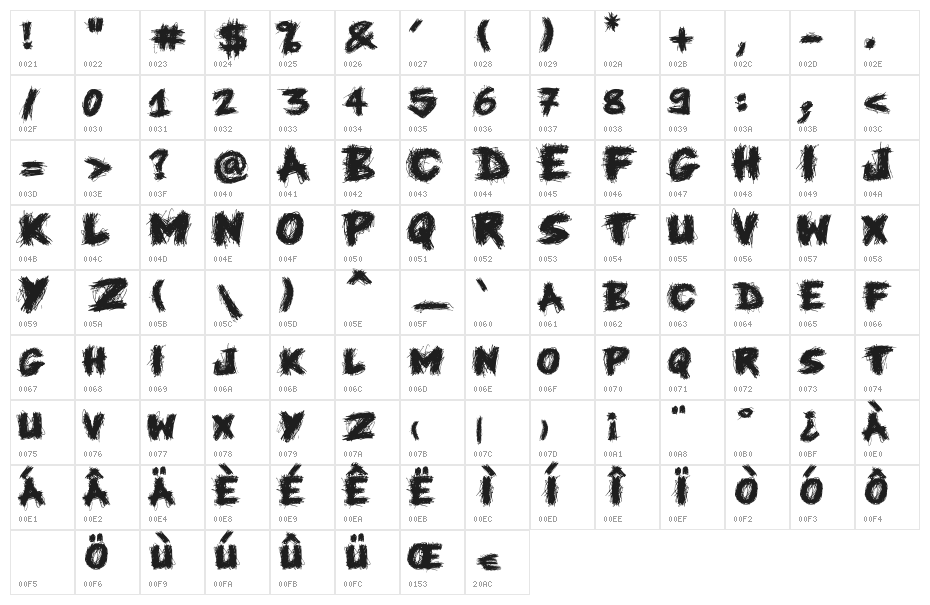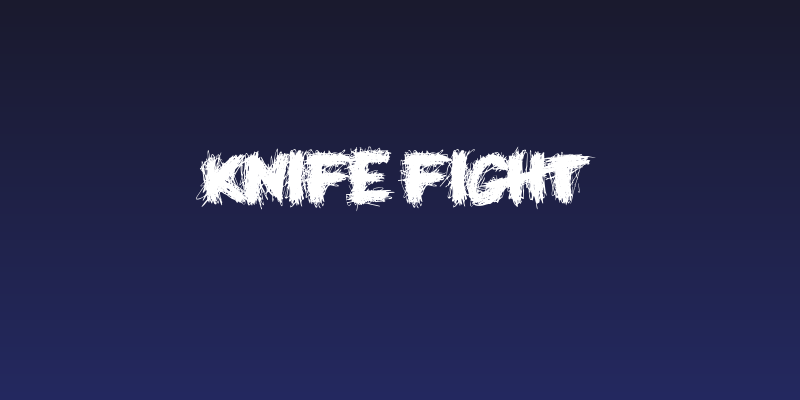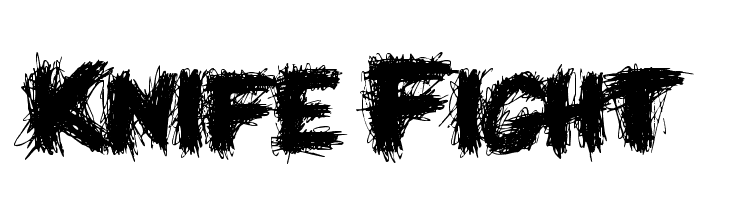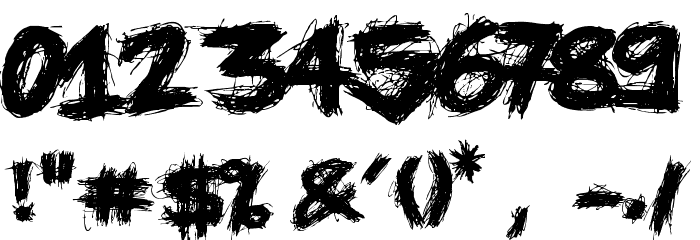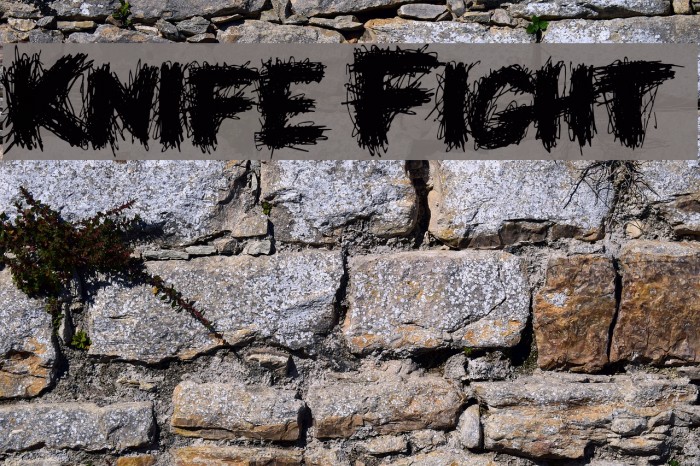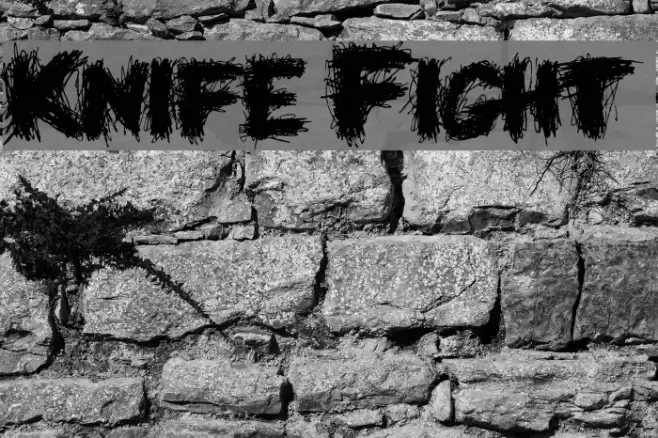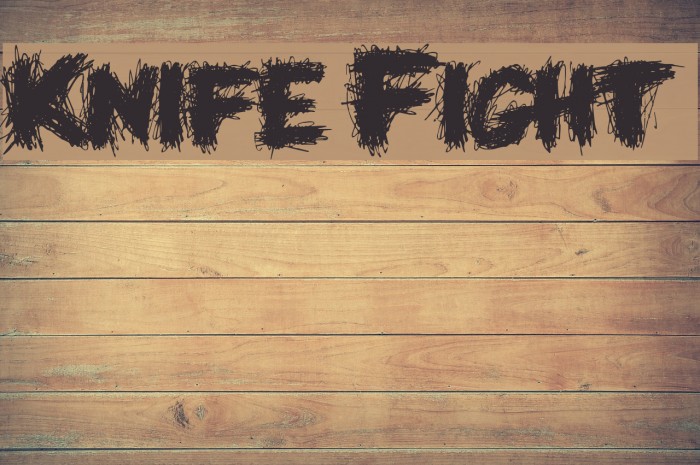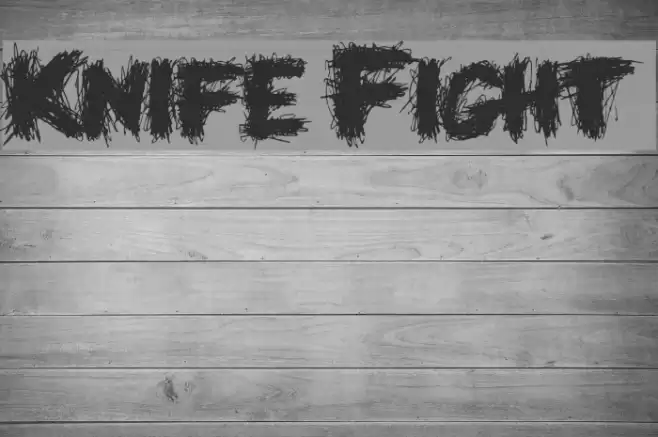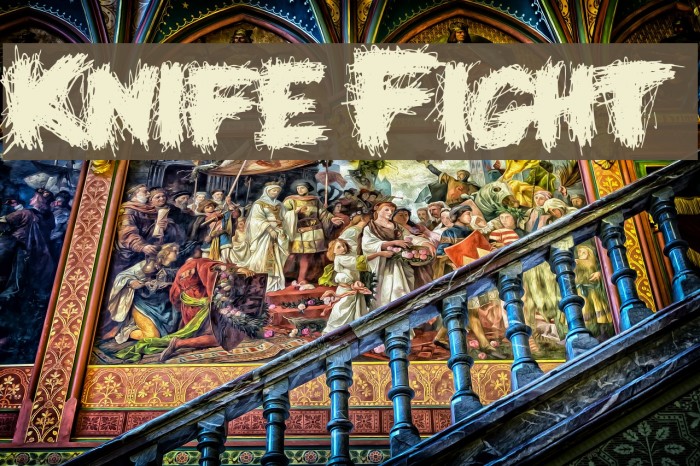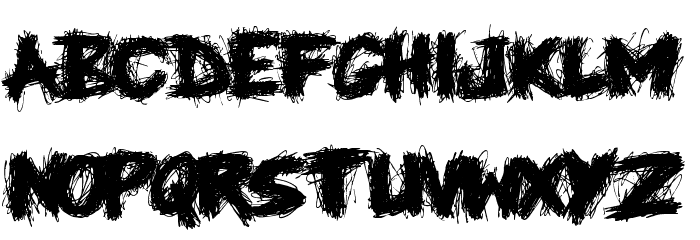
Knife Fight Font
| Style général | Modern, Grunge |
| Projets proposés | Ideal for edgy posters, album covers, graffiti art, or any design needing a rebellious touch. |